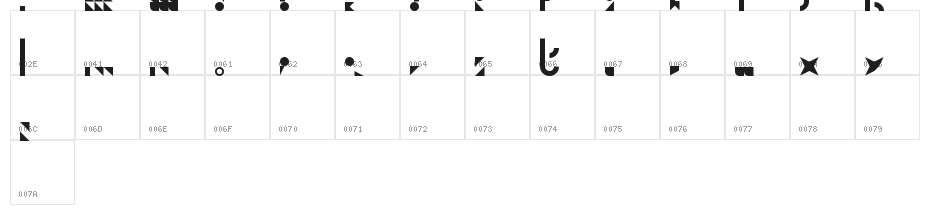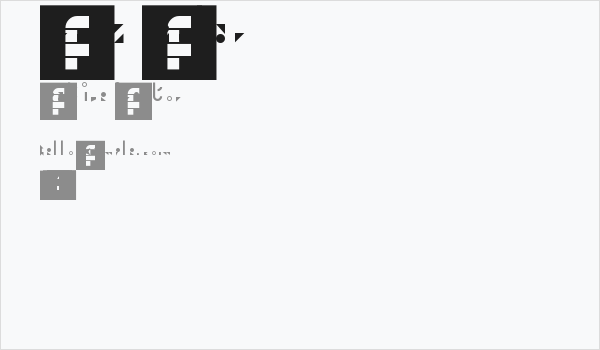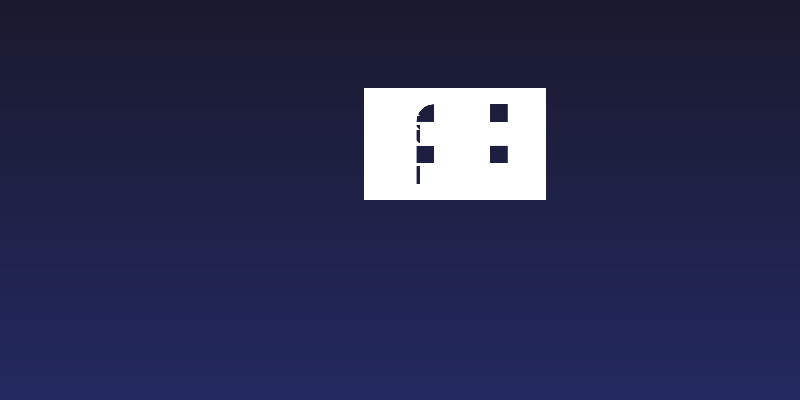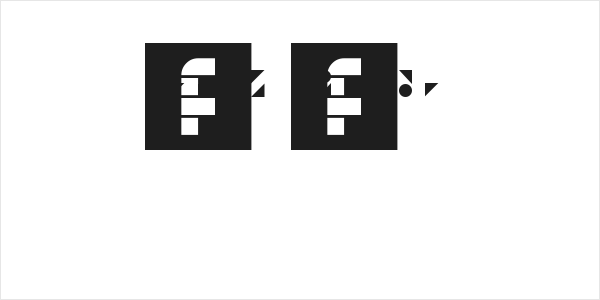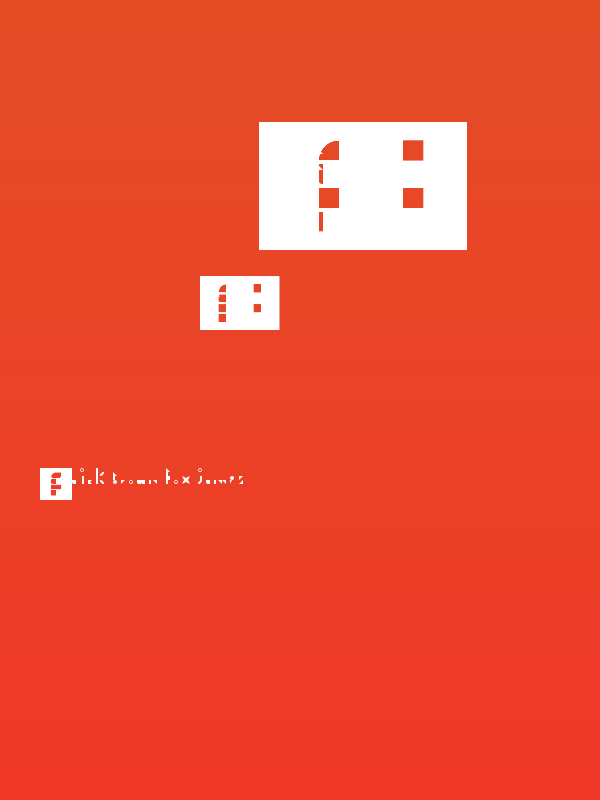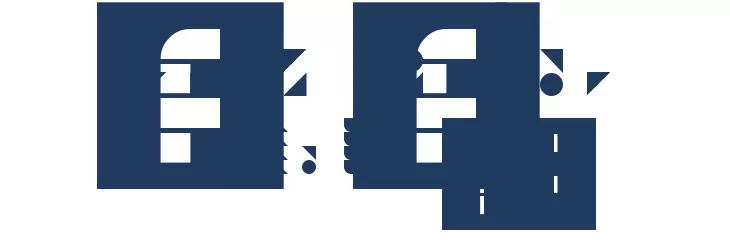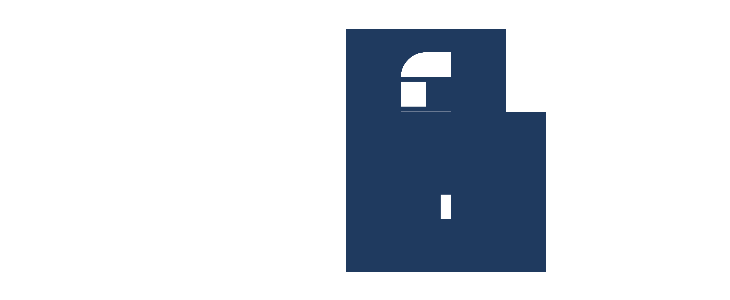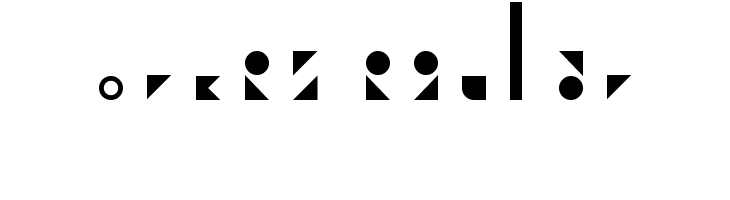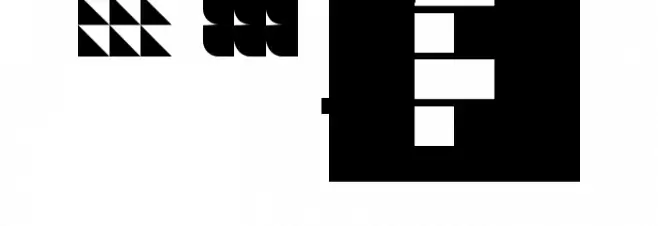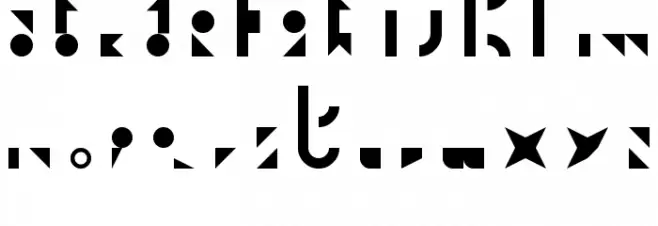
Forces Regular Font
| Proiecte propuse | This font is perfect for projects that require a futuristic or digital aesthetic, such as tech company logos, video game titles, or sci-fi movie posters. |